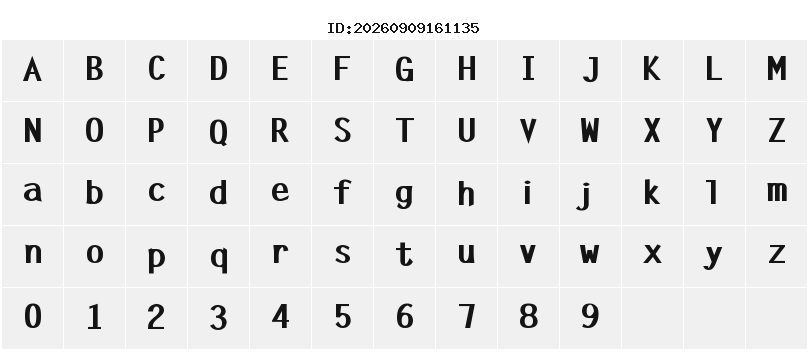
• Font Name: 机甲宋
• Font Style: 粗体
• Font ID: IPfonts:MechSong_BaiHu
• Full Font Name: 机甲宋白虎号
• PostScript Name: MechSong-BaiHu
• Designer: 曾颖欣
• Manufacturer: IPfonts
• Description: 由小欣大萌制作的机甲宋。修长机甲身, 柔美宋体魂。 刚毅添英气, 柔刚相济韵。 机甲宋白虎号是以宋体与机甲元素结合字型设计而成,在视觉上形成了强烈的冲击力,给人以深刻的印象。机甲宋白虎号的笔画则经过反复推敲,既符合书法规范,又符合机甲形象的特点。使机甲宋白虎号字型独特而有科技感。